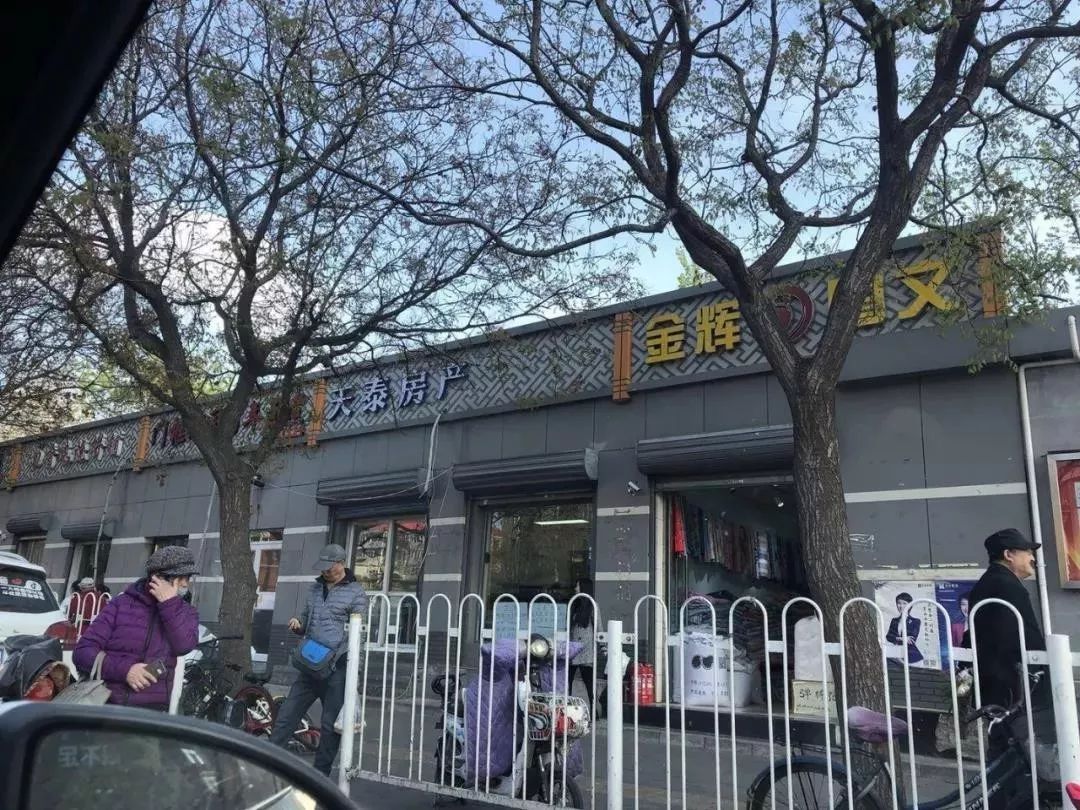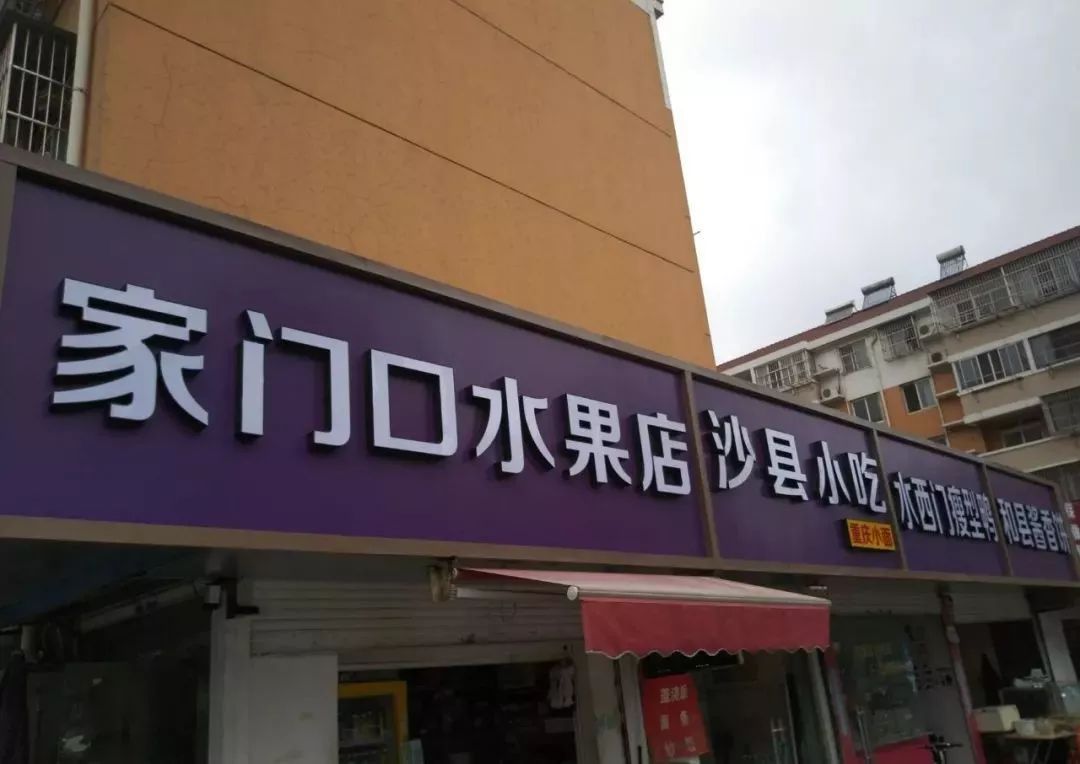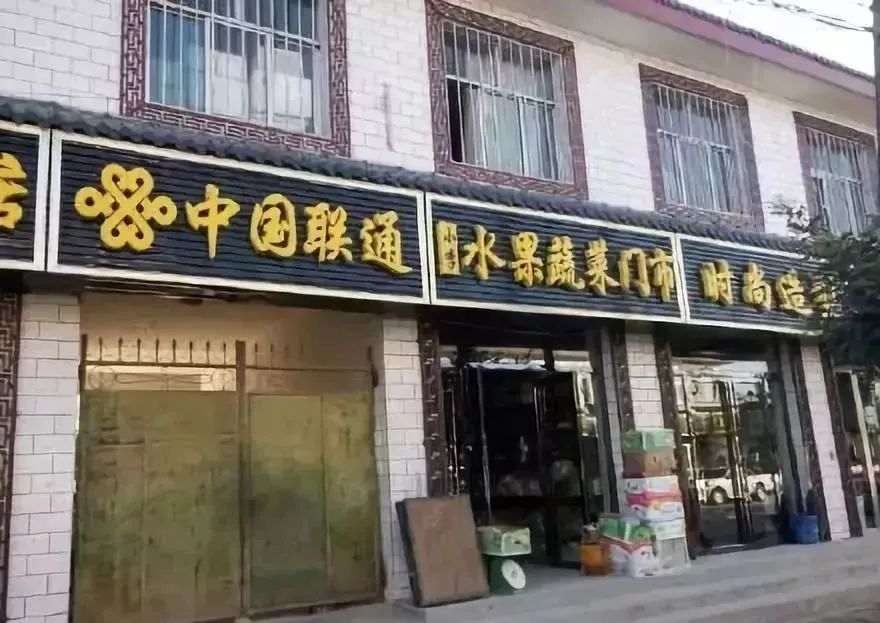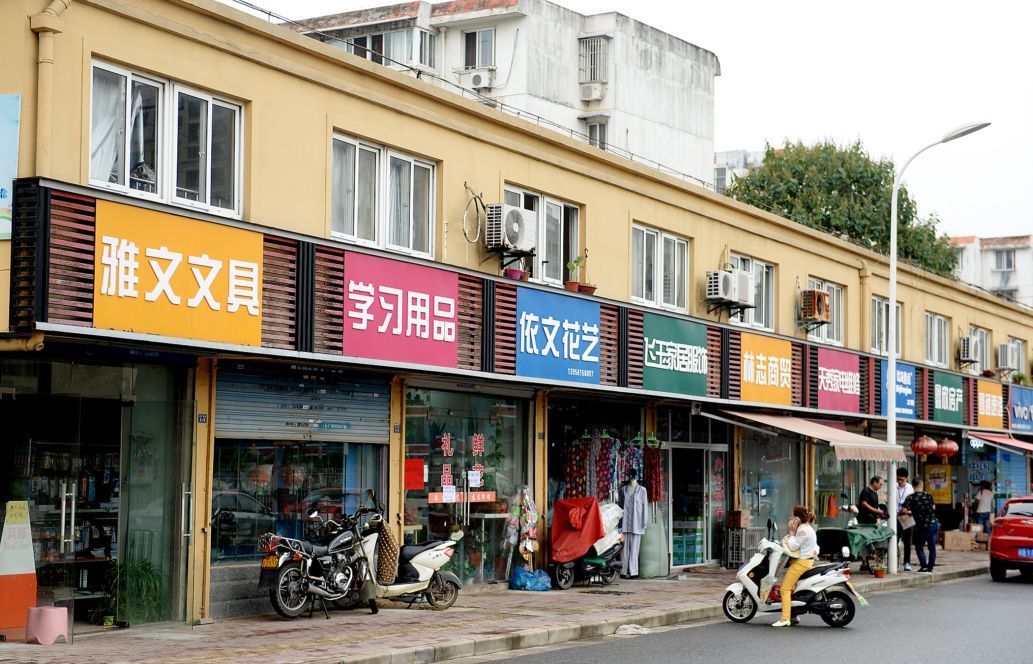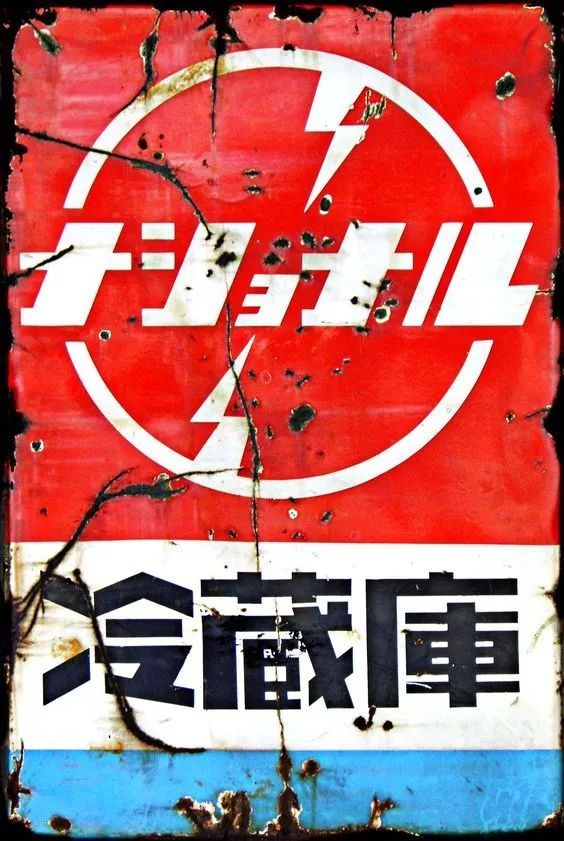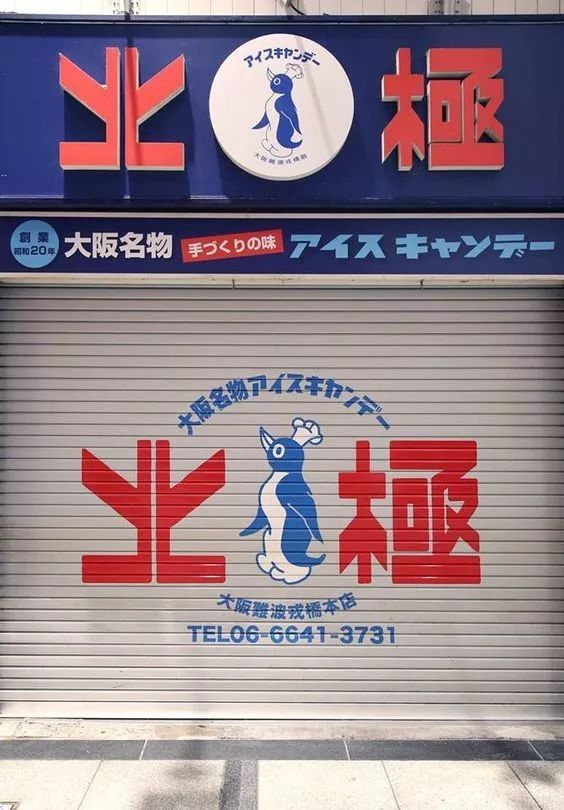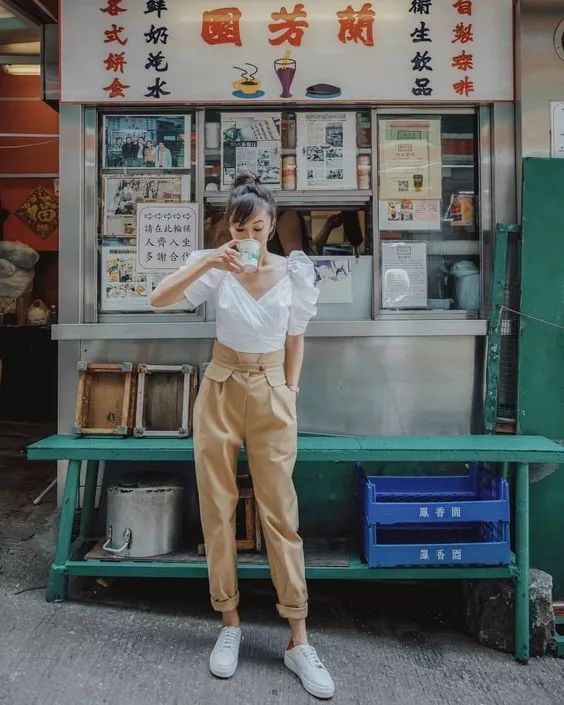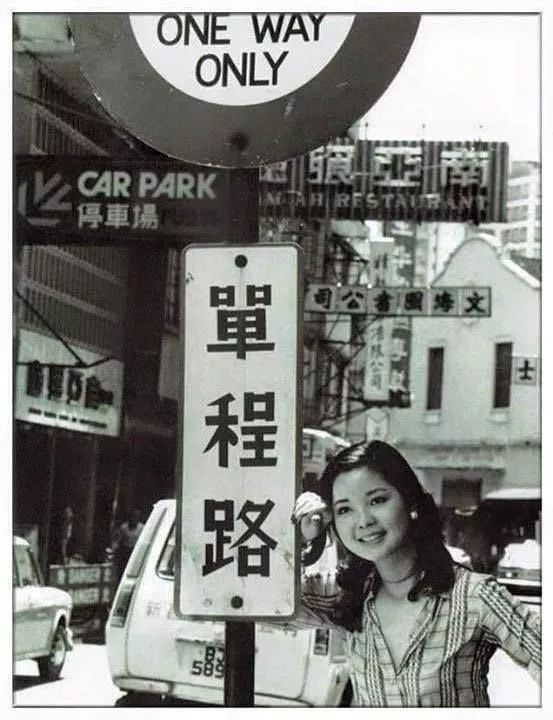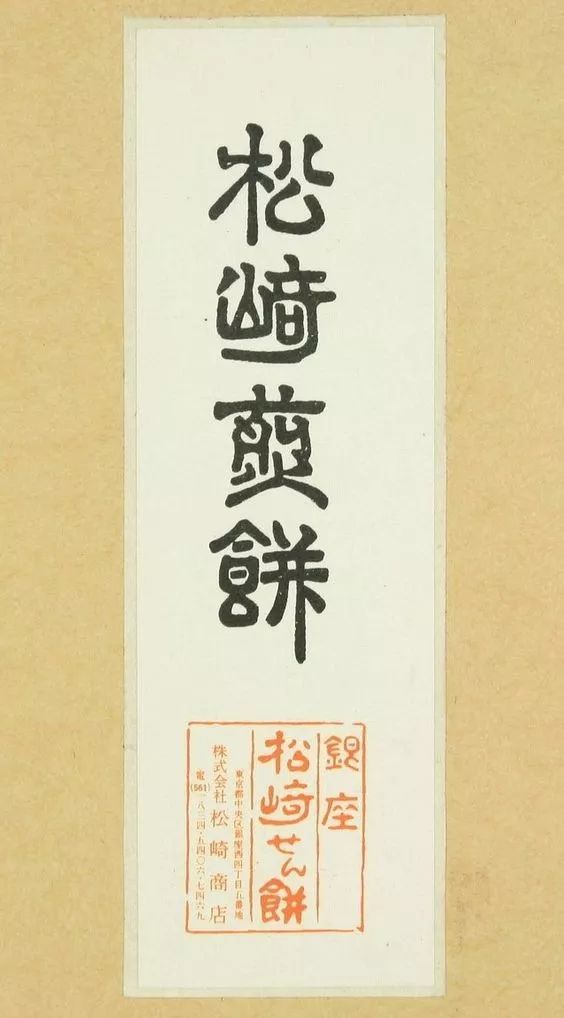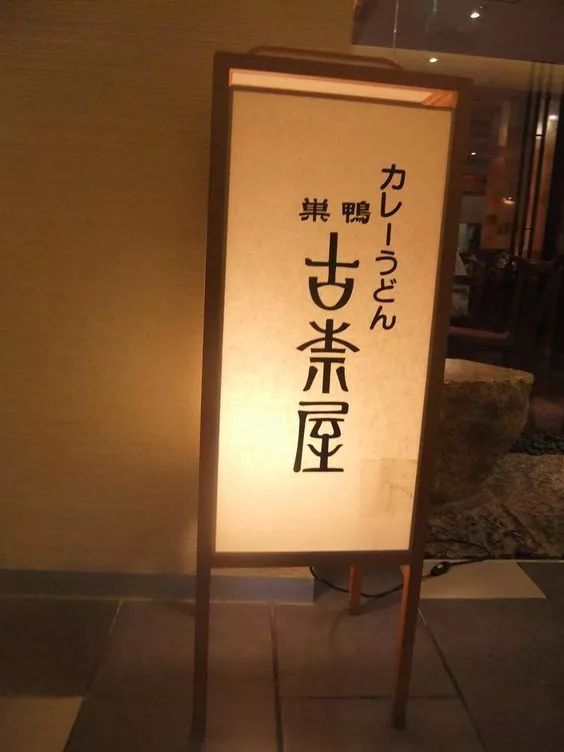
街头字体的魅力
你的城市有这种被疯狂吐槽的清明节风格店招吗?
走在中国都市街头,你能够感受到这独一无二的中国式景观,几乎没有一座城市能够幸免,就连历史文化底蕴很强的一线城市北京,也被统一的招牌毁掉了城市本该有的包容和美感。
其它城市的随便贴一些图感受一下:
OMG!我的眼睛要瞎了!一句话概括:
城市统一了店招,失去了灵魂。
相比这千篇一律的丑陋的店招,再看看那些极其富有创造性的街头字体,哪怕是已经锈迹斑斑的手工字体,也显得有生气的多,接下来就让我们来感受下街头字体的魅力。
【 每日牛乳 】
古老的建筑搭配简约醒目的字体,却没有格格不入之感
反而能够融为一体
【 冷藏库 】
简洁而有力量的字体
【 停放 】
锈迹斑斑,反倒更有故事和灵魂
【 給油所 】
无论是名字还是字体都是那么的接地气
【 雪糕 】
那时候的雪糕,不需要你去超市里去买
总会有一个老大爷骑着自行车把雪糕送到你的家门口
【 北極 】
几何的字形,对称的结构,形式和力量感极强
【 東南布行 】
一个布行的店招,文字看上去像书法名家的作品
而不是现在满大街都是的电脑感痕迹很强的假书法体
【 路吃 】
不经意间的一个小创意
会让人莞尔一笑
【 商店 】
笔画是故意弯曲的吗?
细看原来店字里藏了一个苹果
【 小東門百貨公司 】
看字体设计就能感觉
是一家很有意思的百货公司
【 蘭芳園 】
这样的店招是不是比那些亚克力灯箱的有感觉多了?
【 單程路 】
一代巨星邓丽君等车的地方
【 驾驶员休息室 】
那时候的字体设计多么前卫
几何形式运用非常纯熟
【 劳研馒头 】
一个卖馒头的店竟然如此重视字体设计
【 雪花啤酒 】
那时候的雪花,不比现在的好看吗
【 松崎煎饼 】
这是我见过的最有感觉的煎饼字体
【 古茶屋 】
很有特点的字形,保留了一些篆书的特点
【 古人有云 】
轻松、自在,如在云下田间
【 本日定食 】